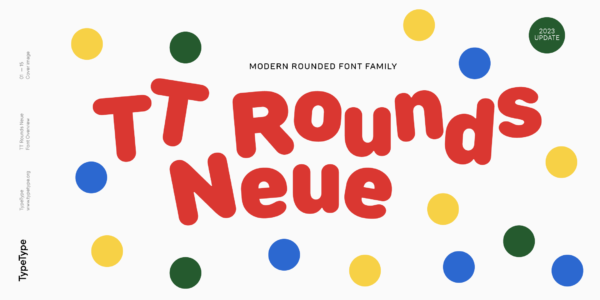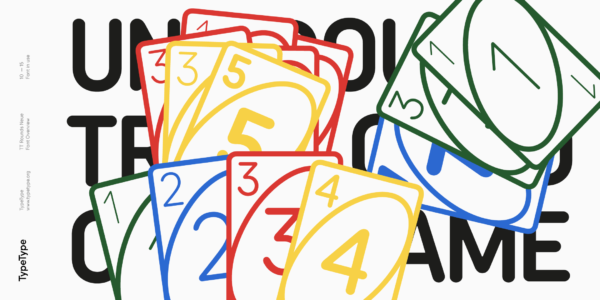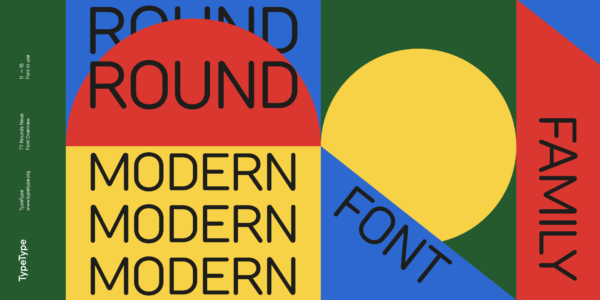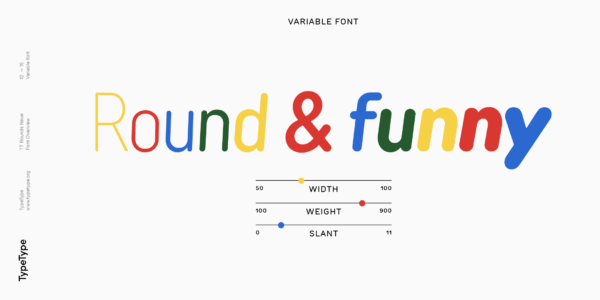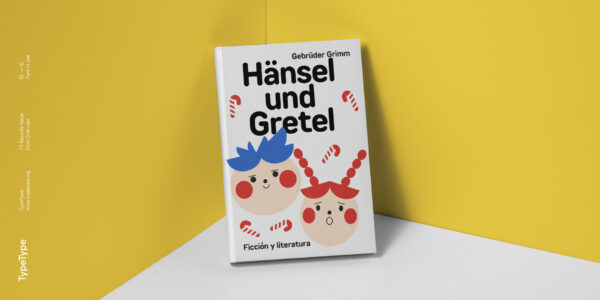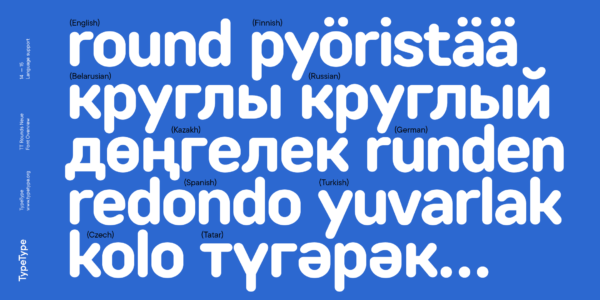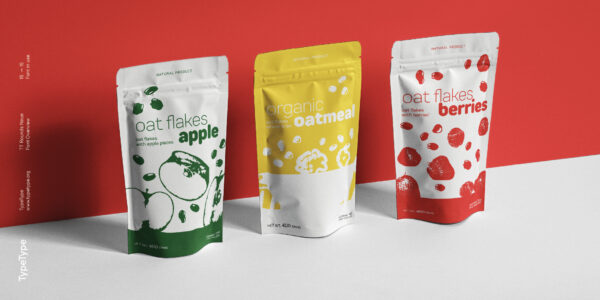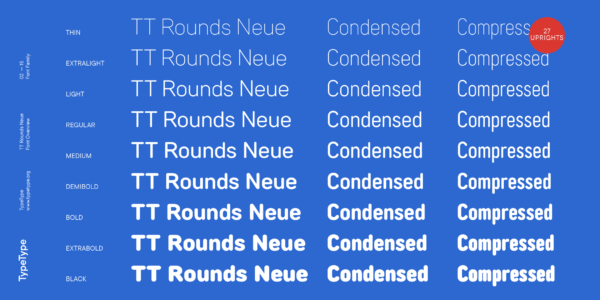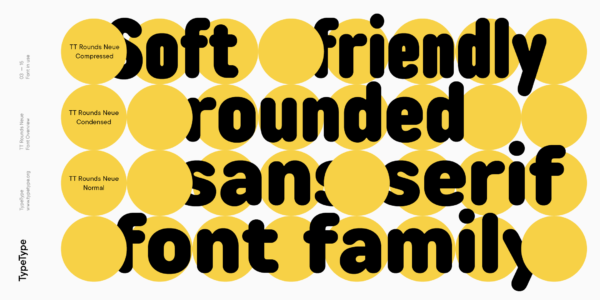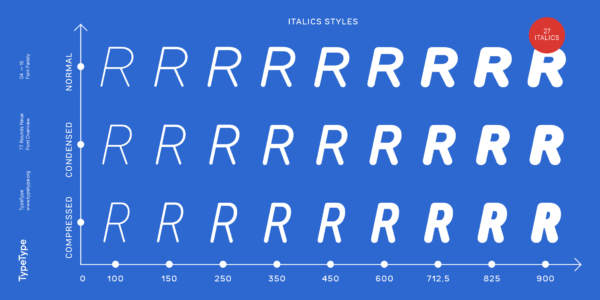
TT Rounds Neue
TT Rounds Neue — ТТ Раундс Нью
Произносится «ТТ Раундс Нью». «Rounds» — производное слово от round, в переводе с английского «круг», «Neue» — в переводе c немецкого «новый». Буквы «TT» являются аббревиатурой названия компании.
TT Rounds Neue — мягкий и дружелюбный гротеск со скруглёнными формами. В тонких начертаниях он выглядит минималистично и нейтрально, а в жирных «надувается» и становится более характерным.
TT Rounds Neue
Мягкий, дружелюбный, скругленный шрифт без засечек
TT Rounds Neue
TT Rounds — это большое шрифтовое семейство, состоящее из 3 подсемейств: Compressed, Condensed и Normal. Благодаря своим скругленным штрихам, шрифт имеет очень мягкий и дружелюбный характер. В 2022 году шрифтовое семейство получило большое обновление, в рамках которого мы расширили знаковый состав, улучшили OpenType фичи, а также собрали полноценный трехосевой вариативный шрифт.
TT Rounds Neue
Шрифт идеально подходит для упаковки овсяной каши и детского питания
TT Rounds Neue
TT Rounds Neue — это 55 шрифтовых начертаний и безграничная палитра возможностей
TT Rounds Neue в дизайне
О гарнитуре TT Rounds Neue
Мы обновили TT Rounds Neue!
TT Rounds Neue — гротеск со скругленными формами. У него мягкий и дружелюбный характер. В тонких начертаниях шрифт выглядит довольно минималистично и нейтрально: скругленные окончания штрихов становятся практически незаметными, на первый план выходят плавные линии. В жирных начертаниях TT Rounds Neue «надувается» и максимально проявляет всю свою округлость, приобретая инфантильные черты.
В обновлённую гарнитуру входит вариативный шрифт, способный меняться по трем осям: ширине, весу и наклону. Используя его, вы можете смело экспериментировать и создавать по-настоящему уникальные проекты!
Мы сделали новую версию TT Rounds Neue ещё функциональнее и удобнее, усовершенствовав технические параметры шрифта и дополнив кассовый состав. В частности, добавили дополнительные знаки расширенной латиницы и кириллицы, обновили кернинг и хинтинг.
В разных начертаниях TT Rounds Neue может использоваться как для заголовков, так и для текстового набора. Гарнитура оптимизирована для работы в вебе, ее можно применять в печатной индустрии и в дизайне упаковки. Благодаря своему веселому характеру шрифт отлично подойдет для оформления товаров и услуг для детей: развивающих игр, пищевых продуктов, брендов одежды и т. д. Но этим сфера его применения, конечно, не ограничивается.